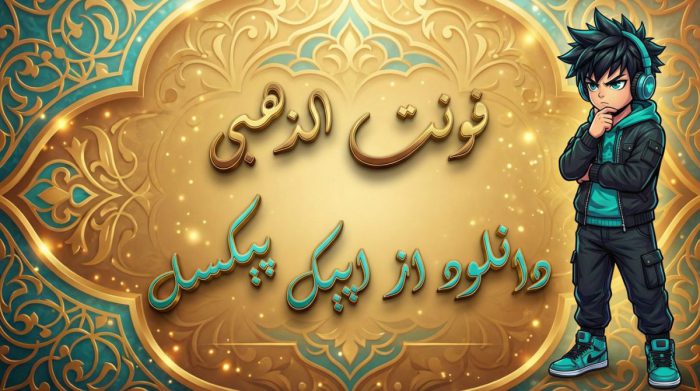
فونت الذهبی و نزار الذهبی (Aldhabi) فونت عربی و فارسی TTF
آیا از فونت های تکراری و بی روح در پروژه های مذهبی و طراحی پوستر خسته شده اید؟ پیدا کردن فونتی که هم اصالت خوشنویسی دستی را داشته باشد و هم در نرم افزارهای مدرن به درستی نمایش داده شود، یک چالش بزرگ است. پکیج فونت الذهبی با ارائه ترکیبات چشم نواز و کشیدگی های هنری، راهکاری ایده آل برای خلق آثاری است که نگاه ها را خیره می کند و به برندینگ شما هویت می بخشد.
- تایپوگرافی خودکار: فونت الذهبی از الگوریتم های هوشمند برای اتصال حروف و ایجاد کشیدگی های متناسب با سبک دیوانی استفاده می کند.
- دو سبک مکمل: نسخه کلاسیک (Aldhabi) برای متون رسمی و مذهبی و نسخه نزار (Nizar Aldhabi) با اصلاحات بصری برای خوانایی بیشتر در رابط های کاربری مدرن.
- بهینه سازی شده برای چاپ: فواصل حروف و ضخامت خطوط به گونه ای تنظیم شده که در چاپ های با ابعاد بزرگ (مانند بنر و کتیبه) وضوح کامل داشته باشد.
- ترکیبات جایگزین (Alternates): دسترسی به فرم های مختلف یک حرف برای ایجاد تنوع در طراحی های لوگو و تیتر.